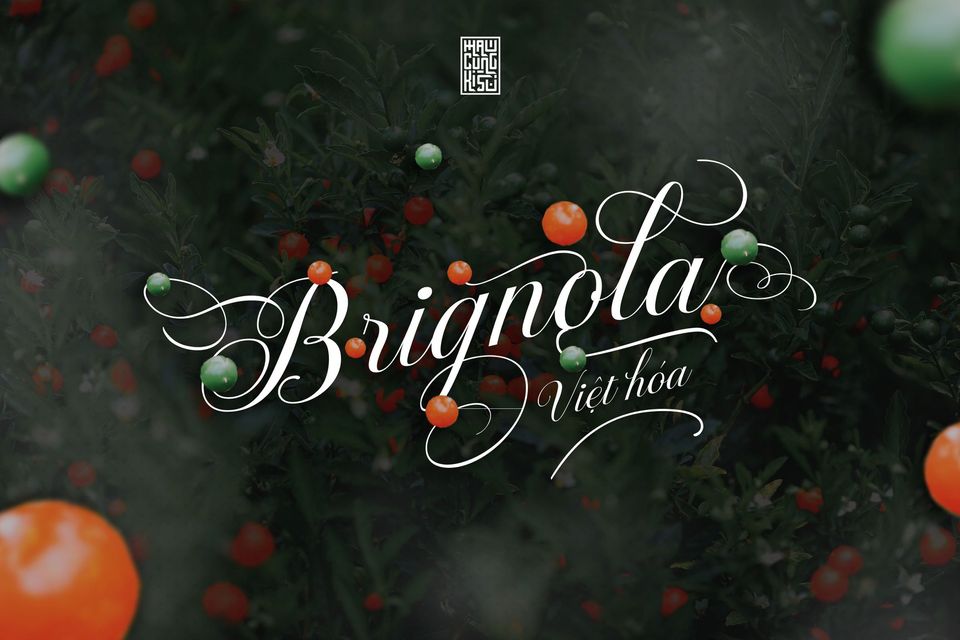
Tuyệt phẩm Font Việt hóa MTD Brignola PUA Script: Tải miễn phí cho thiết kế và dự án học tập
Trong thế giới thiết kế đồ họa và sáng tạo nội dung, việc lựa chọn font chữ phù hợp có thể tạo nên sự khác biệt lớn. Đối với cộng đồng người Việt Nam, đặc biệt là các bạn học sinh, sinh viên đang chuẩn bị cho các dự án lớn hay kỳ thi tốt nghiệp, một font chữ vừa đẹp mắt, vừa hỗ trợ đầy đủ tiếng Việt là vô cùng cần thiết. Hôm nay, chúng ta sẽ khám phá một tuyệt phẩm đang gây sốt: Font Việt hóa MTD Brignola PUA Script – một lựa chọn hoàn hảo cho những ai tìm kiếm sự tinh tế và chuyên nghiệp. Font chữ này không chỉ mang vẻ đẹp của nghệ thuật viết tay cổ điển mà còn được tối ưu hóa hoàn toàn cho ngôn ngữ tiếng Việt, giúp các tác phẩm của bạn trở nên hoàn hảo mà không lo lỗi font dấu.
Giới thiệu chi tiết về Font Việt hóa MTD Brignola PUA Script và những điểm mạnh vượt trội
MTD Brignola PUA Script là một font chữ script (kiểu viết tay) được thiết kế bởi những nghệ nhân có tay nghề cao, nổi tiếng với sự mềm mại, duyên dáng và tính kết nối liền mạch giữa các ký tự. Đây là một phông chữ cao cấp thường được sử dụng trong các ấn phẩm đòi hỏi sự sang trọng như thiệp cưới, bao bì sản phẩm cao cấp, hoặc logo thương hiệu. Tuy nhiên, phiên bản gốc thường thiếu các ký tự tiếng Việt có dấu. Đây chính là lúc giá trị của quá trình Việt hóa được thể hiện rõ nét.
Phiên bản Font Việt hóa MTD Brignola PUA Script đã được các chuyên gia tinh chỉnh cẩn thận, thêm vào hệ thống dấu tiếng Việt (thanh, huyền, sắc, hỏi, ngã, nặng) mà vẫn giữ nguyên được vẻ đẹp và tỷ lệ gốc của font. Đặc biệt, việc font này tích hợp PUA (Private Use Area) cho phép người dùng dễ dàng truy cập và sử dụng các ký tự mở rộng, ký tự thay thế (swash, stylistic alternates) để tạo ra các thiết kế cá nhân hóa một cách dễ dàng nhất trên các phần mềm thiết kế chuyên nghiệp. Đây là yếu tố then chốt giúp sinh viên và nhà thiết kế tiết kiệm thời gian khi xử lý các chi tiết phức tạp, nhất là trong giai đoạn nước rút của các đồ án tốt nghiệp quan trọng.
Đặc điểm giúp MTD Brignola PUA Script trở nên khác biệt
- Vẻ đẹp viết tay cổ điển: Mô phỏng chữ viết tay thư pháp, tạo cảm giác cá nhân hóa và ấm áp, rất phù hợp cho các ấn phẩm mang tính kỷ niệm hoặc thiệp mời cao cấp.
- Hỗ trợ PUA đầy đủ: Cho phép sử dụng hàng trăm glyphs và biến thể nâng cao mà không cần đến các công cụ phức tạp, tối ưu hóa cho công việc thiết kế đồ họa.
- Tương thích tiếng Việt hoàn hảo: Đã được căn chỉnh kỹ lưỡng, đảm bảo dấu tiếng Việt không bị nhảy hay mất cân đối, giải quyết triệt để vấn đề lỗi font chữ thường gặp.
- Tính ứng dụng cao: Phù hợp từ các dự án học thuật, báo cáo, đến các ấn phẩm thương mại cao cấp, đáp ứng nhu cầu đa dạng của người dùng.
Tối ưu hóa thiết kế và dự án học tập với Font Việt hóa MTD Brignola PUA Script
Đối với học sinh, sinh viên, đặc biệt là những bạn đang học chuyên ngành thiết kế đồ họa, truyền thông, hay đơn giản là cần tạo ra một bài thuyết trình (slide presentation) ấn tượng cho kỳ thi hoặc báo cáo cuối kỳ, việc sở hữu một bộ font chữ độc đáo là lợi thế lớn. MTD Brignola PUA Script mang lại sự chuyên nghiệp, tinh tế mà các font chữ mặc định khó có thể sánh bằng. Nó giúp tiêu đề của các đồ án tốt nghiệp, các bài luận văn, hay thậm chí là bìa sổ tay cá nhân trở nên nổi bật và thu hút sự chú ý ngay từ cái nhìn đầu tiên của hội đồng giám khảo hoặc người đọc.
Bên cạnh đó, các giáo viên hoặc nhà trường có thể sử dụng font này để thiết kế các loại giấy khen, chứng chỉ, hoặc thiệp mời sự kiện quan trọng như lễ bế giảng hay lễ trao bằng tốt nghiệp. Sự thanh lịch của phông chữ này truyền tải một thông điệp trang trọng và đáng nhớ, rất phù hợp với môi trường giáo dục cao cấp. Việc font đã được Việt hóa cũng đồng nghĩa với việc tiết kiệm thời gian chỉnh sửa font lỗi, giúp quá trình làm việc trở nên suôn sẻ hơn rất nhiều, từ đó nâng cao hiệu suất làm việc.
Làm thế nào để sinh viên tận dụng tối đa Font MTD Brignola?
Sinh viên có thể áp dụng font chữ này vào nhiều khía cạnh của cuộc sống học tập và cá nhân, đặc biệt khi cần tạo ra sự khác biệt và đẳng cấp:
- Thiết kế bìa sách hoặc tạp chí học thuật, giúp sản phẩm trông chuyên nghiệp như xuất bản phẩm thực thụ.
- Tạo chữ ký điện tử (e-signature) độc đáo và chuyên nghiệp, sử dụng trong email hoặc các văn bản quan trọng.
- Làm thiệp mời điện tử cho các sự kiện của trường hoặc lớp với phong cách sang trọng, khác biệt.
- Sử dụng làm tiêu đề phụ (sub-headline) trong các bản báo cáo chính thức để tăng tính thẩm mỹ và dễ đọc.
Tóm lại, Font Việt hóa MTD Brignola PUA Script là một tài sản vô giá đối với bất kỳ ai đang làm việc trong lĩnh vực sáng tạo, từ các nhà thiết kế chuyên nghiệp cho đến các bạn học sinh đang chuẩn bị bước vào mùa thi cử và làm đồ án. Với vẻ đẹp thư pháp quyến rũ và sự hỗ trợ tiếng Việt tuyệt đối, nó chắc chắn sẽ nâng tầm chất lượng các sản phẩm của bạn, giúp bạn đạt được kết quả ấn tượng nhất. Đừng ngần ngại tải về và trải nghiệm sự khác biệt mà font chữ cao cấp này mang lại cho dự án sắp tới của bạn!